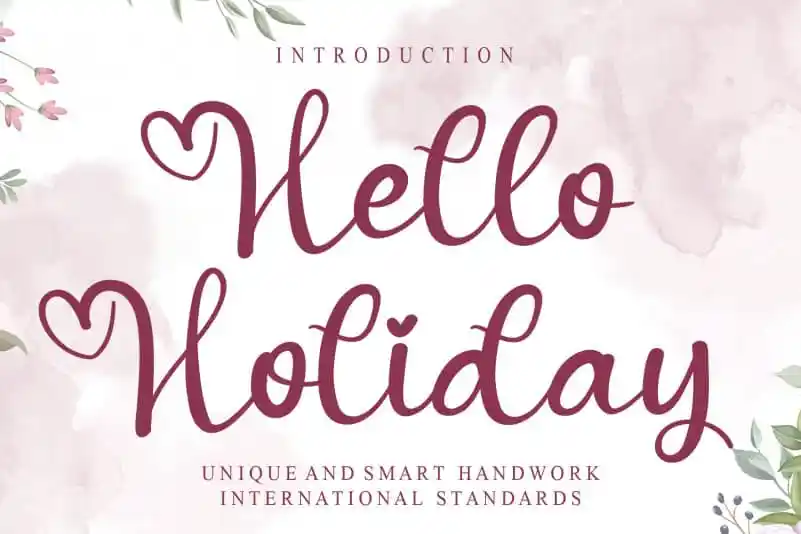
Hello Holiday Calligraphy Font – Download Grátis
A fonte “Hello Holiday Calligraphy Font” é uma criação única para designers que desejam adicionar um toque especial aos seus projetos visuais durante as férias. Esta fonte script é perfeita para criar mensagens emotivas e singelas, ideal para cartões de aniversário, cartazes de evento ou qualquer outro material promocional especial a ser usado durante o período festivo. Com sua caligrafia elaborada e elegante, essa fonte oferece uma experiência única aos designers. Ela é perfeitamente adequada para personalizar mensagens de chamadas telefônicas de aniversário ou cartões de Natal com um ar de criatividade e sofisticação. A designer creativeletter não apenas criou esta fonte, mas também a projetou para oferecer uma experiência de escrita fluente, tornando-a ideal para designers que estão sempre em busca de novas maneiras de expressar seu trabalho. Uma das marcas mais interessantes desta fonte é sua flexibilidade. Seja ela usada para criar cartões personalizados ou incorporada em um layout de jornal, a “Hello Holiday Calligraphy Font” irá trazer vida e colorida à qualquer projeto visual que você estiver desenvolvendo durante as férias do final de ano.